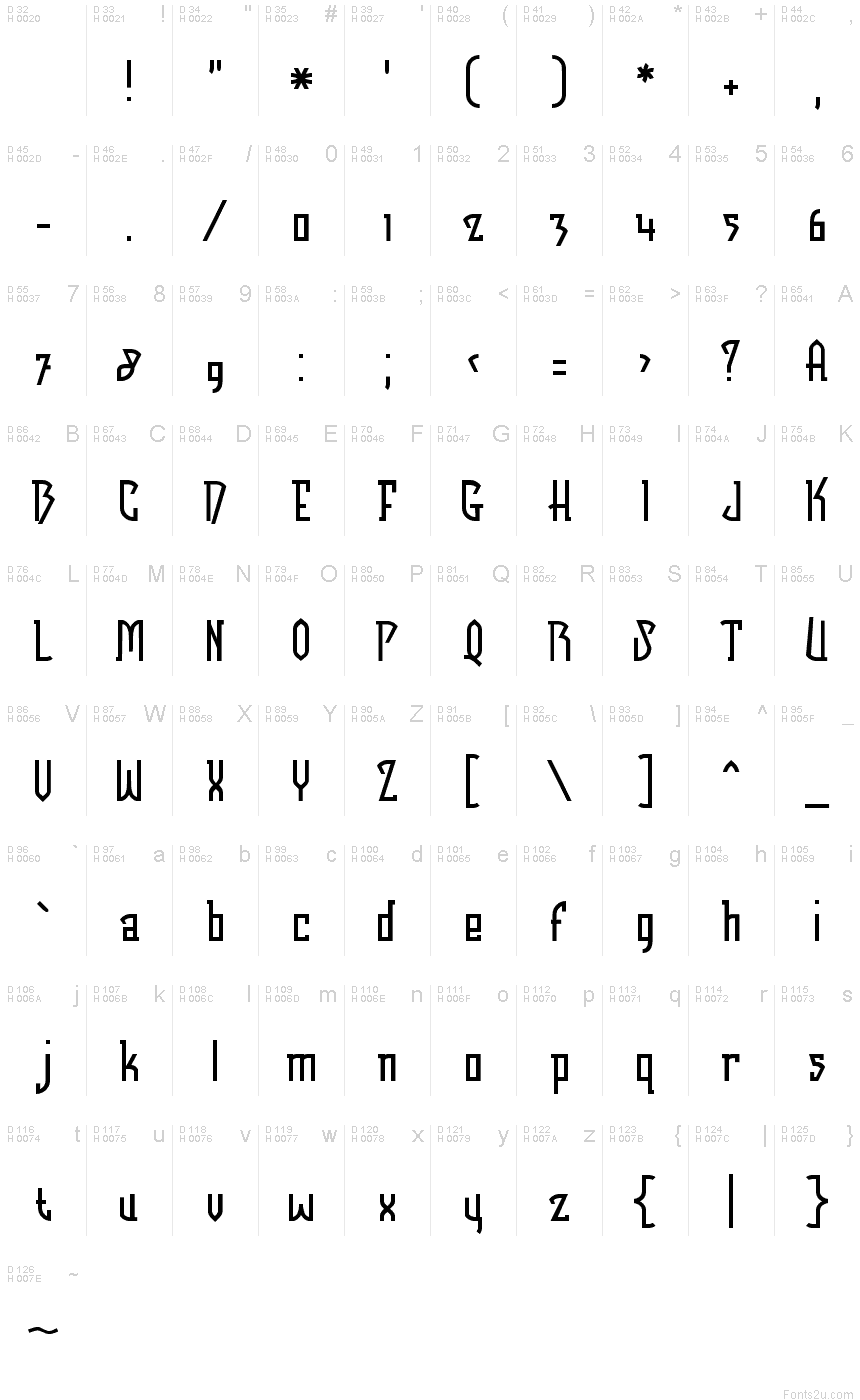
Futurex Bob od Joebob Graff-x 2000 je bezplatné futuristické patkové písmo s výrazným mechanickým nádechem. Vysoké, tuhé tahy a hranaté spoje mu dodávají silný, monolitický dojem, zatímco mírně drsné, „inkoustové“ obrysy brání tomu, aby působilo příliš klinicky. Písmena do sebe zapadají jako modulární systém a vytvářejí kompaktní slovní tvary, které působí spíše zkonstruovaně než jen nakresleně.
S Futurex Bob získáte úderný sci-fi hlas, který skvěle funguje v názvech her, na plakátech technických akcí, v experimentálním brandingu, na obálkách knih či komiksů a ve výrazné grafice pro sociální sítě. Toto bezplatné písmo vynikne při velkých velikostech, kde se jeho masivní geometrie dokáže skutečně propojit. Pro doplňující text ho kombinujte s čistým geometrickým bezpatkovým písmem a FuturexBob si nechte na titulky a krátké fráze, abyste zachovali čitelnost a působivost.